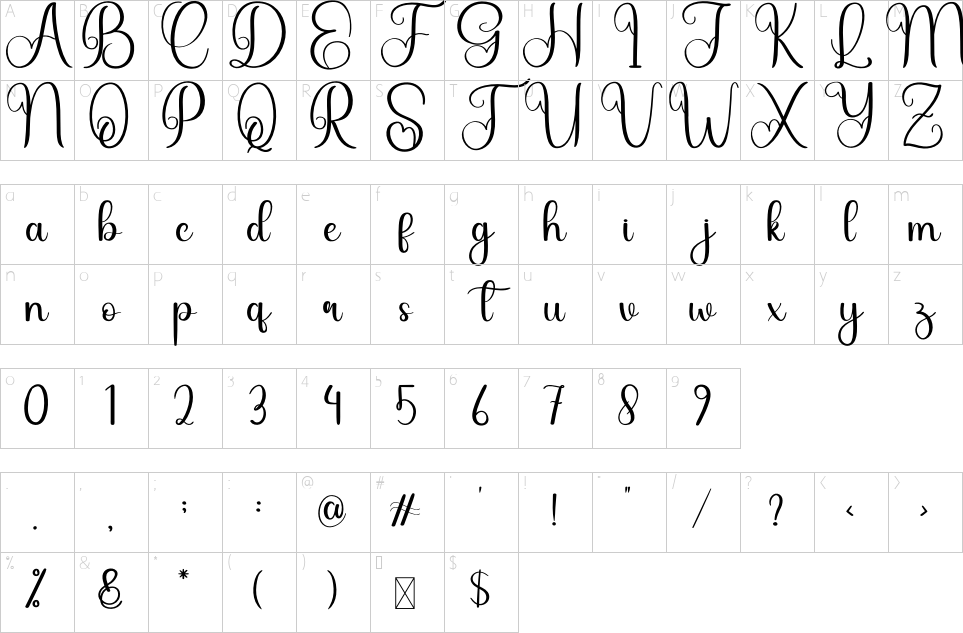
Descubra o charme da Angelina, uma fonte elegante e versátil projetada para adicionar um toque atraente a seus projetos digitais. Angelina foi criada pelo designer desconhecido scratchones e tem impressionado muitos com sua simplicidade e modernidade. Esta fonte, disponível tanto para Windows quanto para Mac, foi projetada para complementar diversas estéticas, desde sites de estilo minimalista até editoriais de moda. Com 2,295 downloads, a Angelina já provou ser uma escolha inteligente para profissionais e aficionados no design digital. Se você busca uma fonte que combine sofisticação com facilidade de uso, Angelina pode ser sua escolha perfeita.